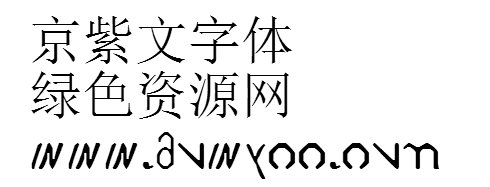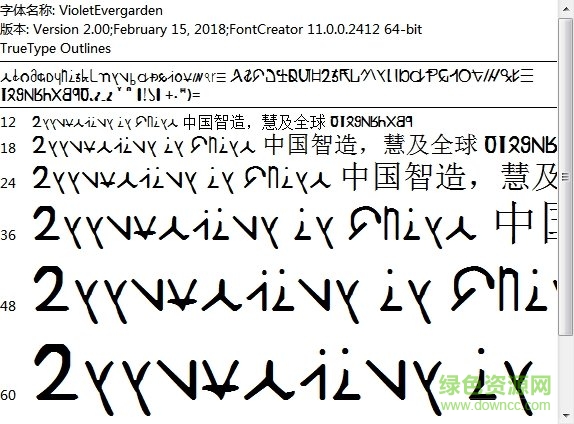
京紫文字體是網(wǎng)友根據(jù)紫羅蘭永恒花園動漫打字機畫面制作的一款日系動漫字體,將26個英文字母進行變形,感受最經(jīng)典最具特色的京紫文字,喜歡的朋友就來綠色資源網(wǎng)搶先收藏吧!
僅制作了26對大小寫字母和10個數(shù)字,符號因為時間精力等原因沒有制作。
2.0制作完成!
全部小寫字母加入,字體全部重做調(diào)整單字大小,數(shù)字0和括號修正,加入數(shù)字1